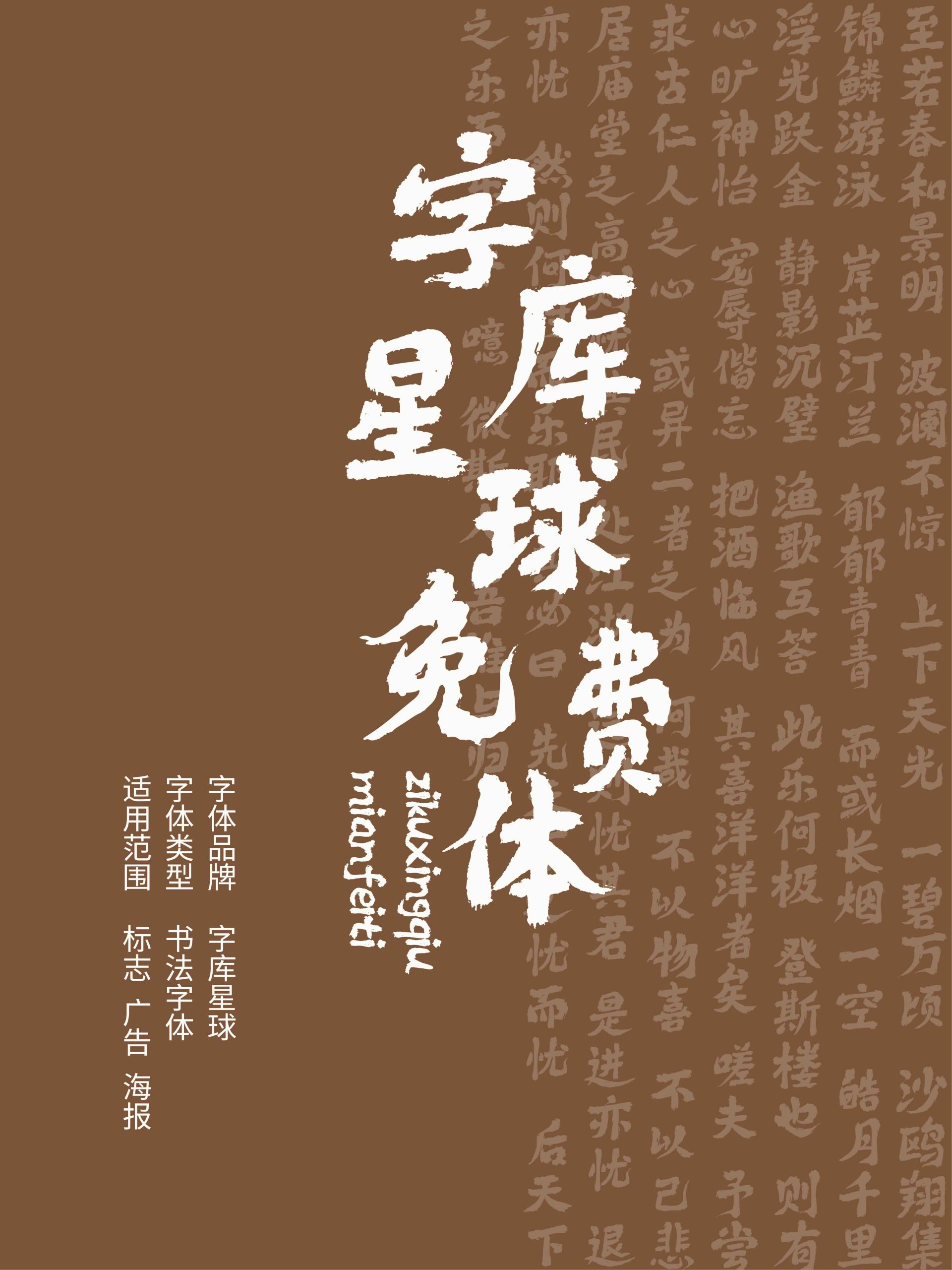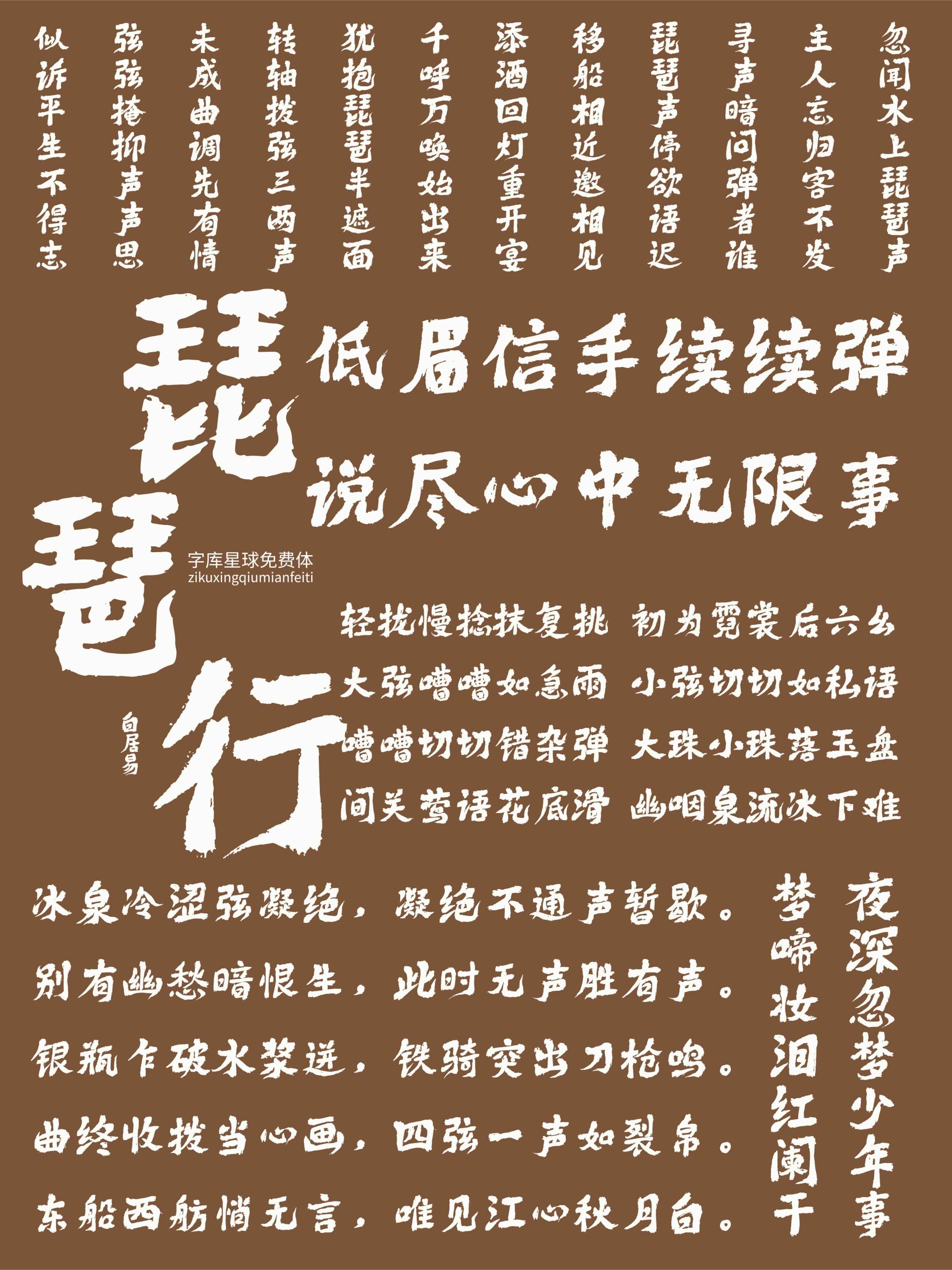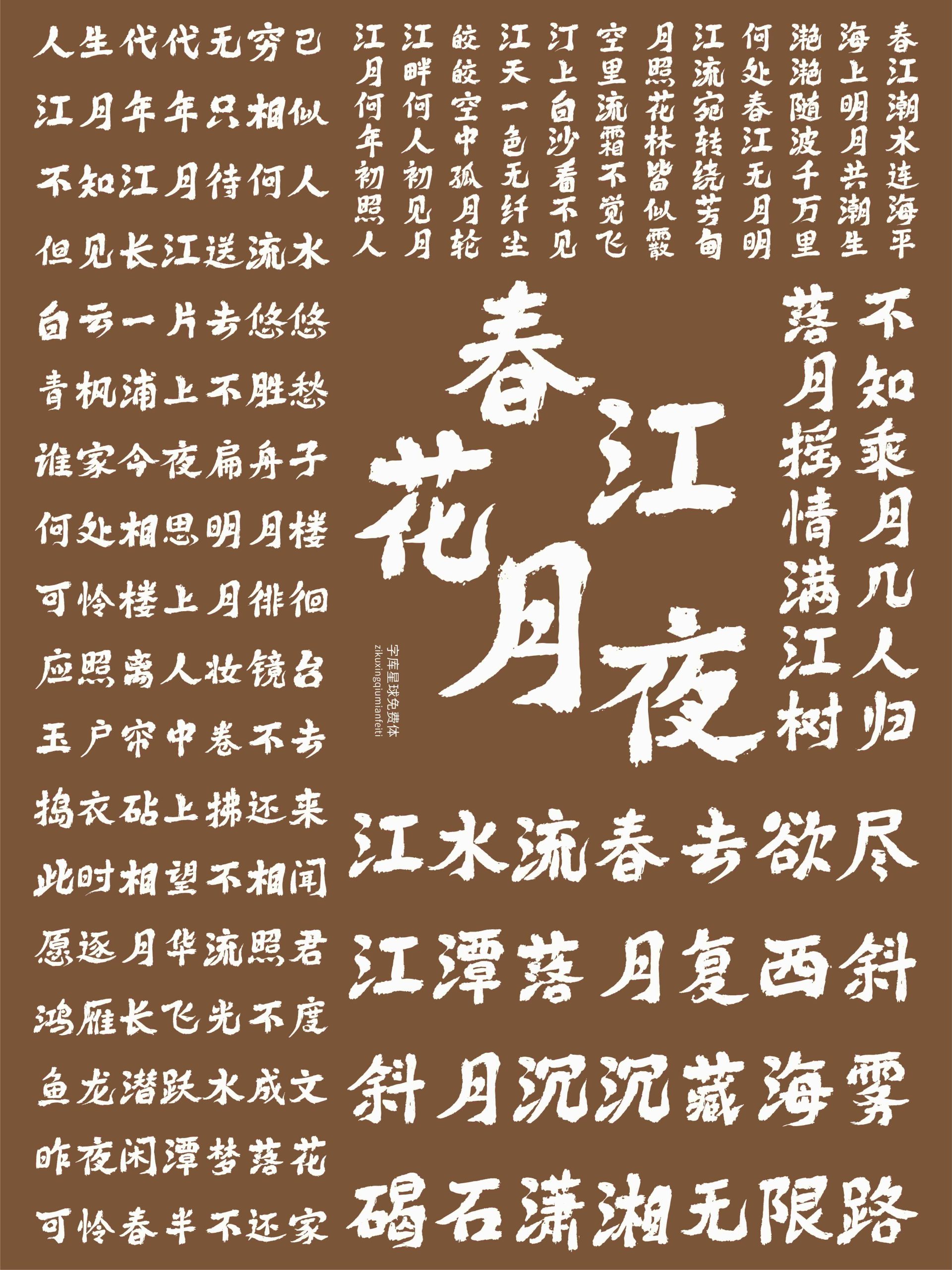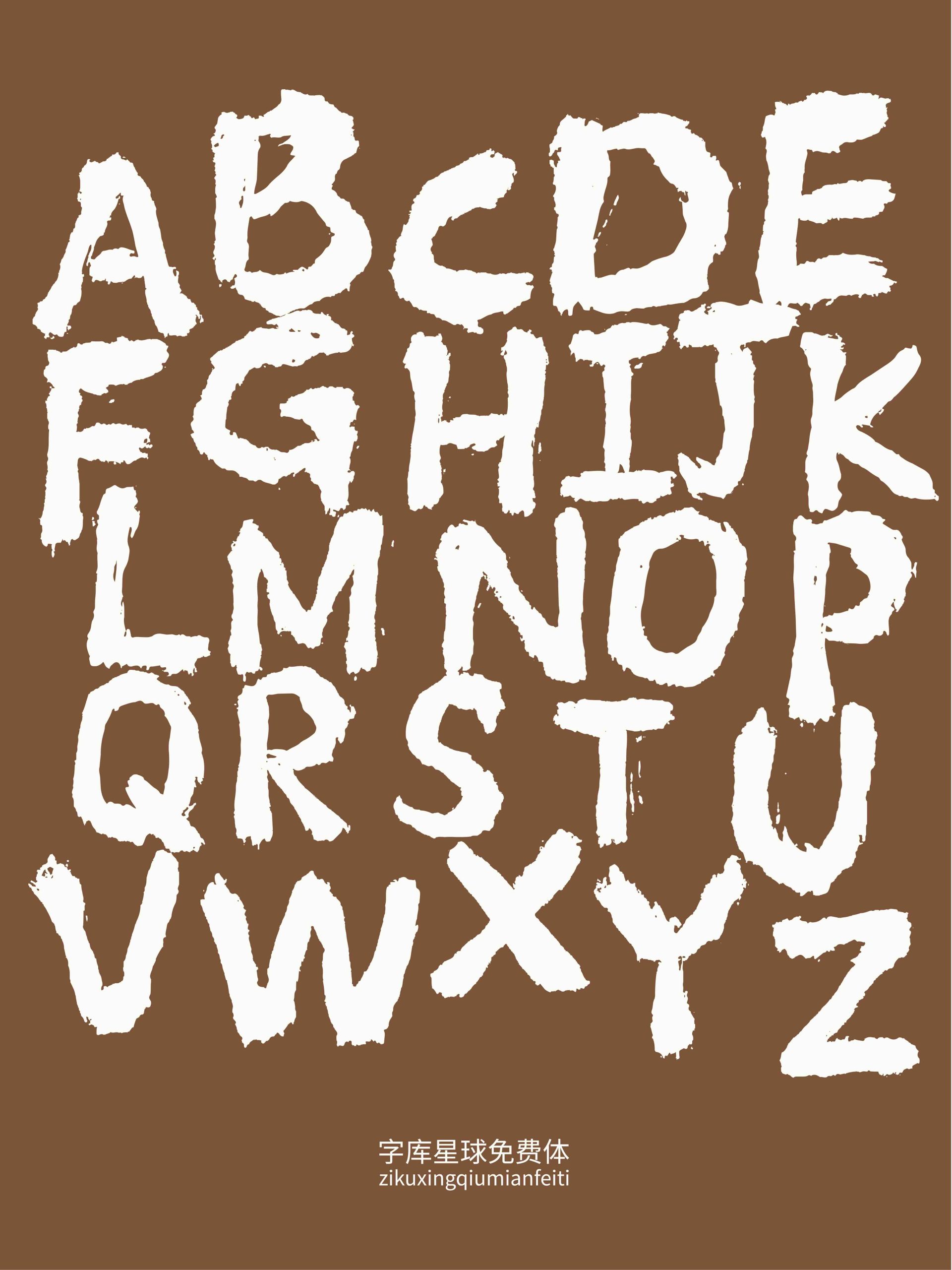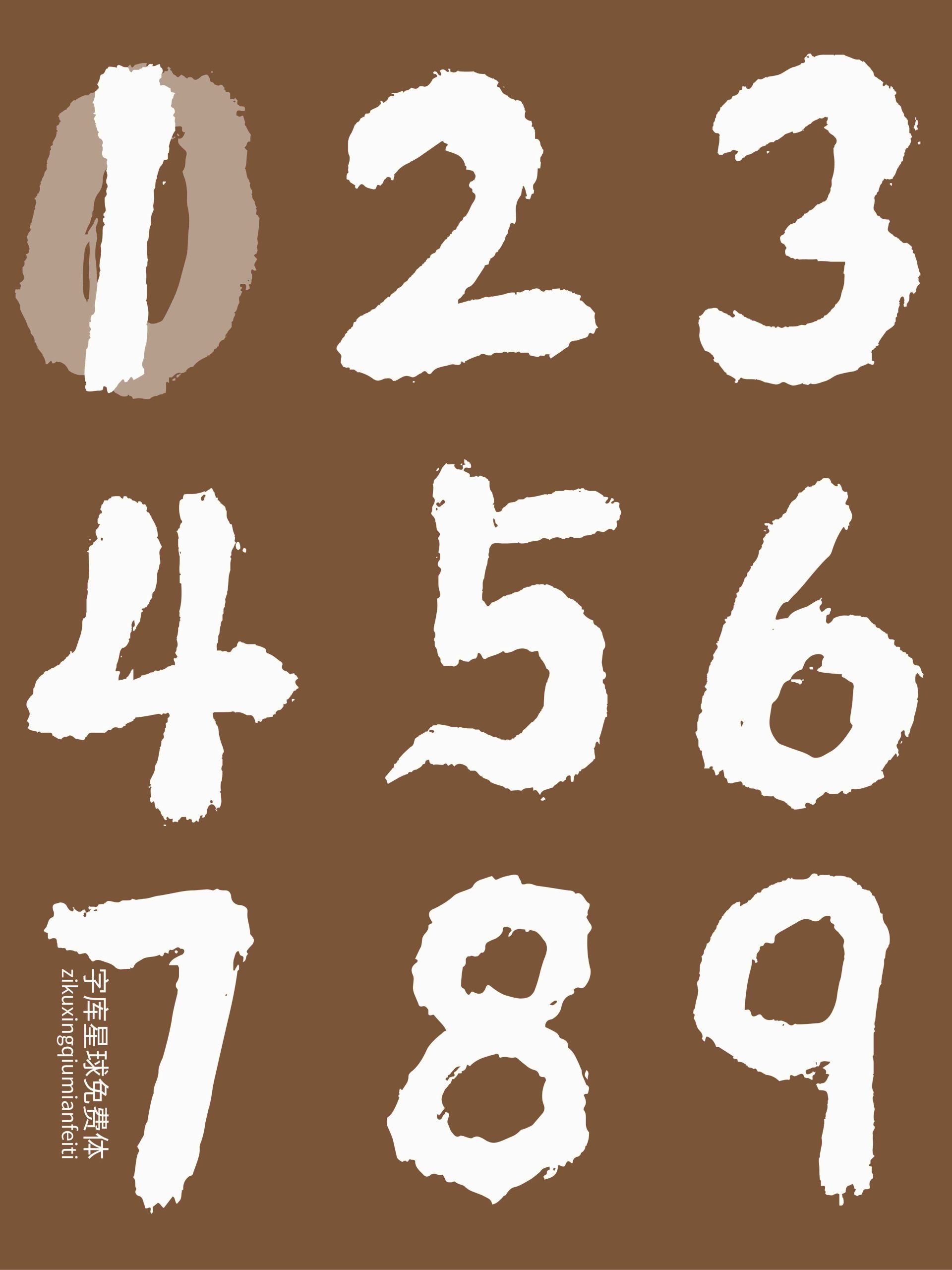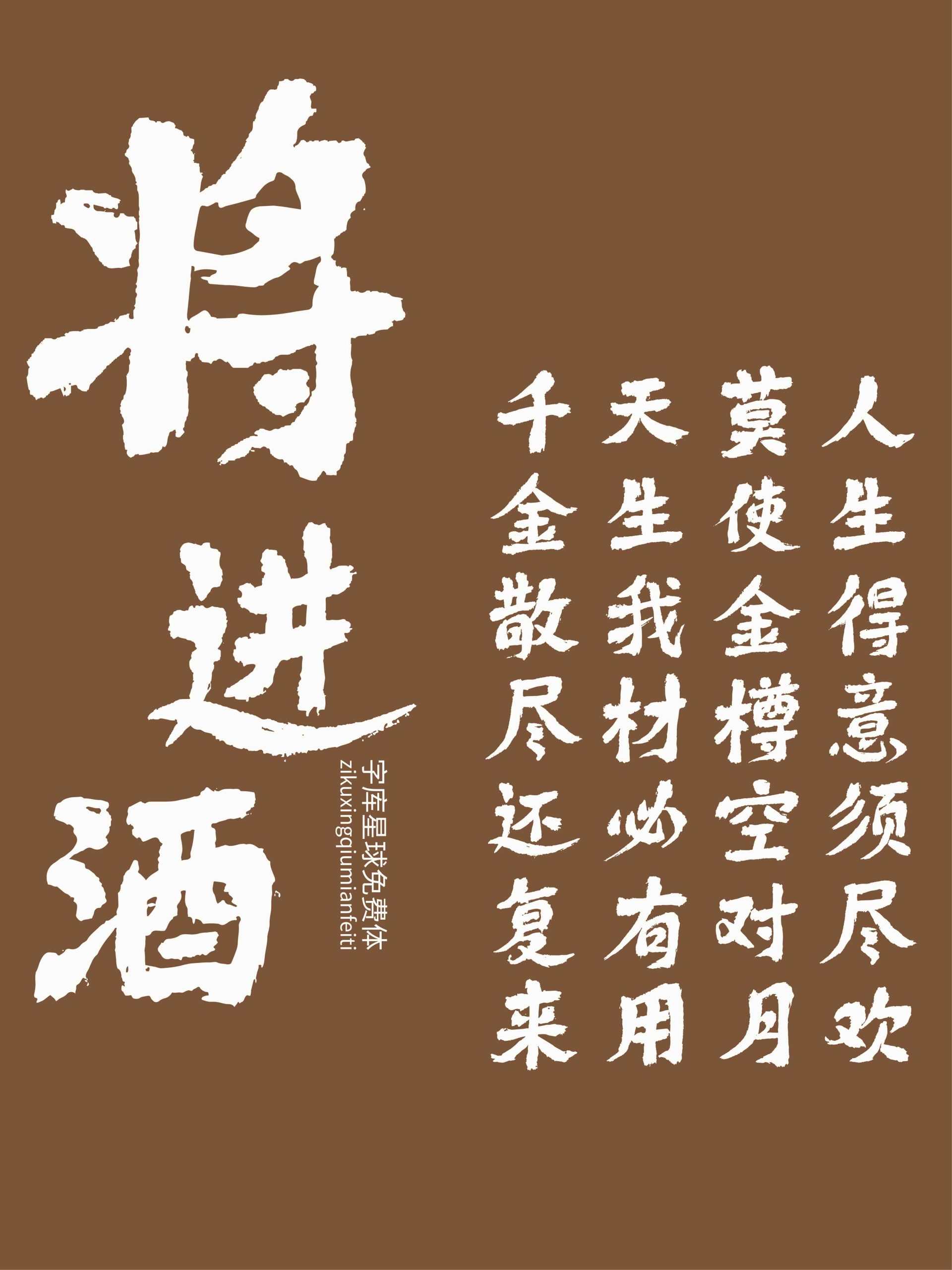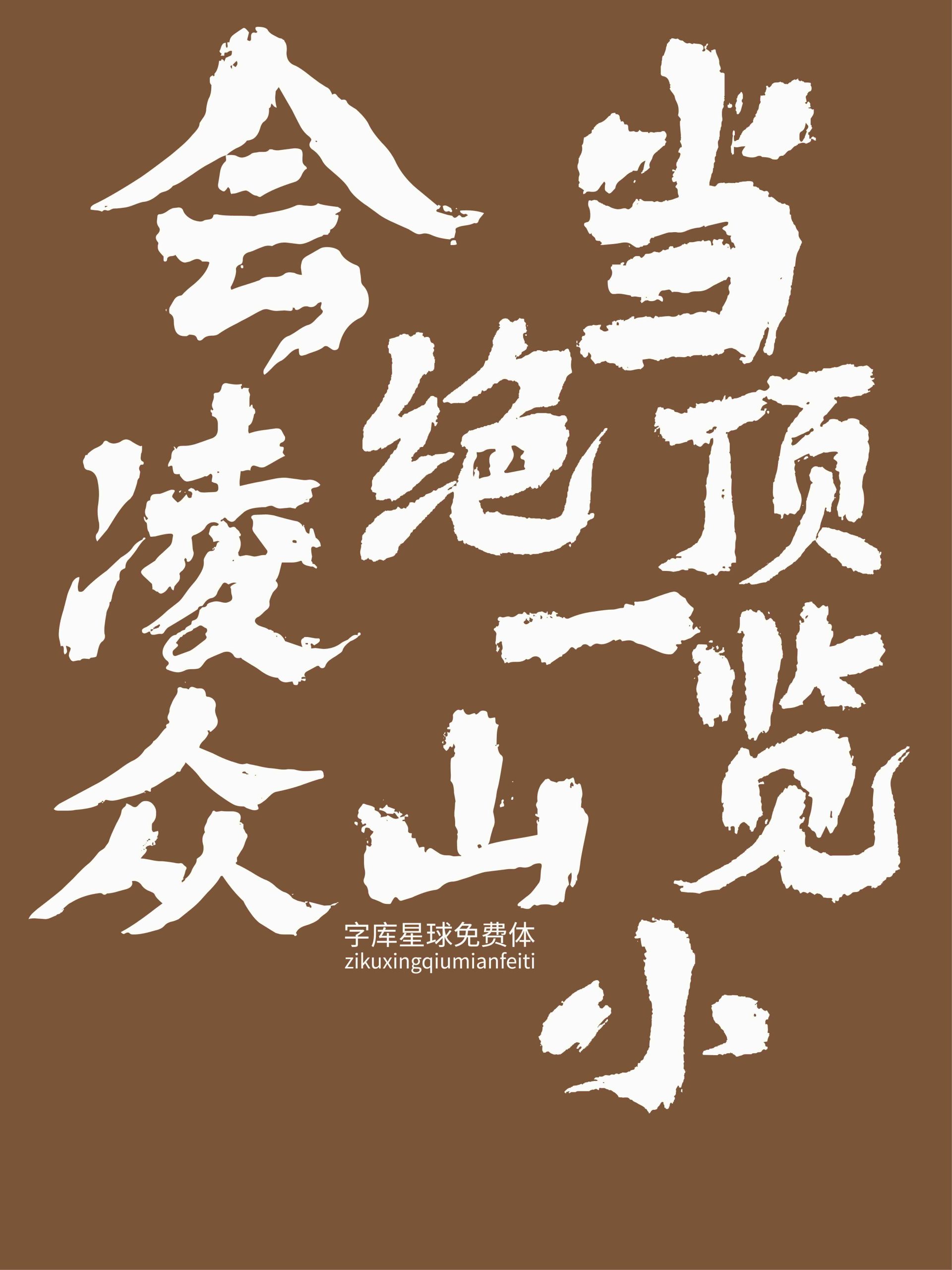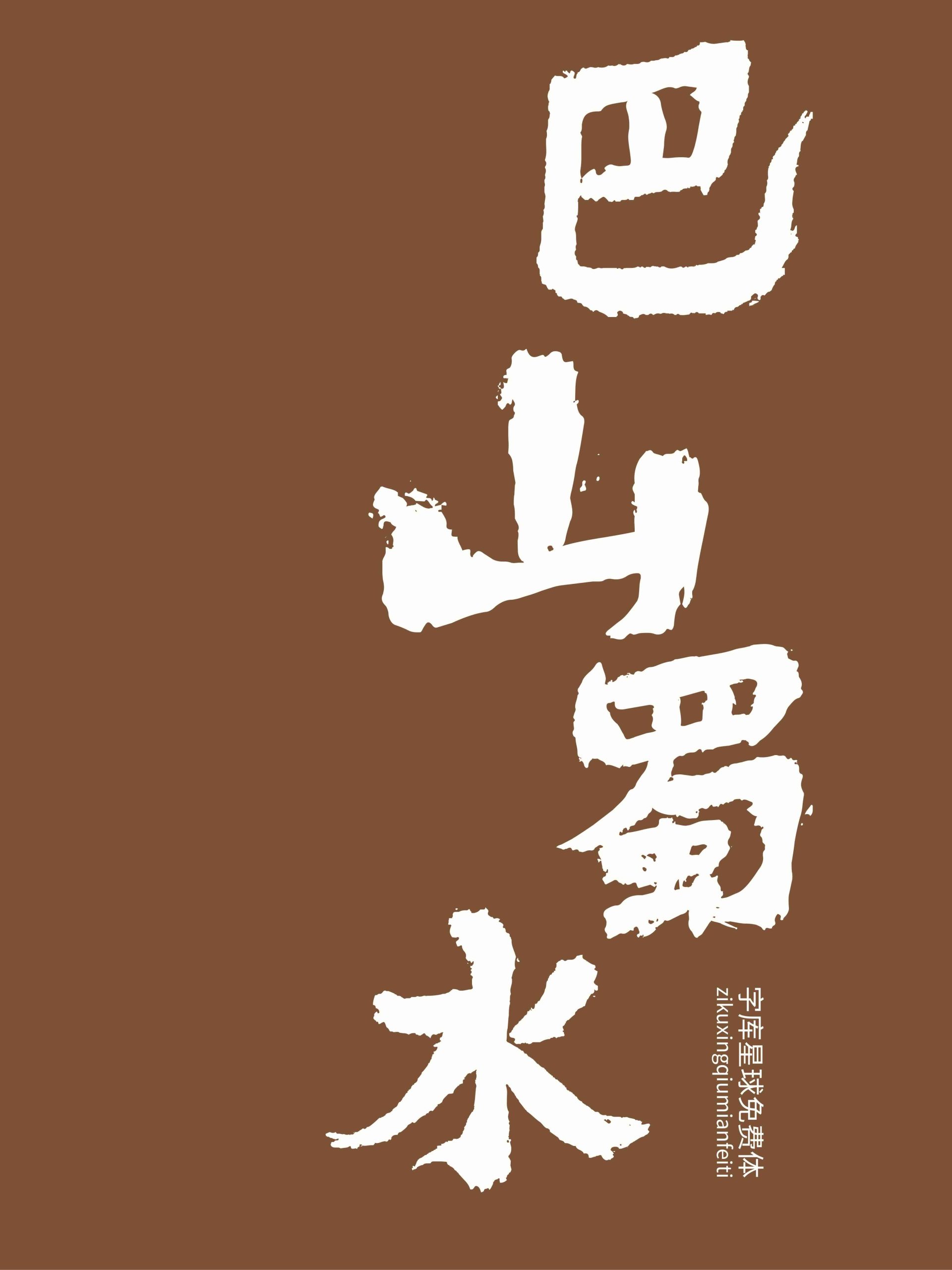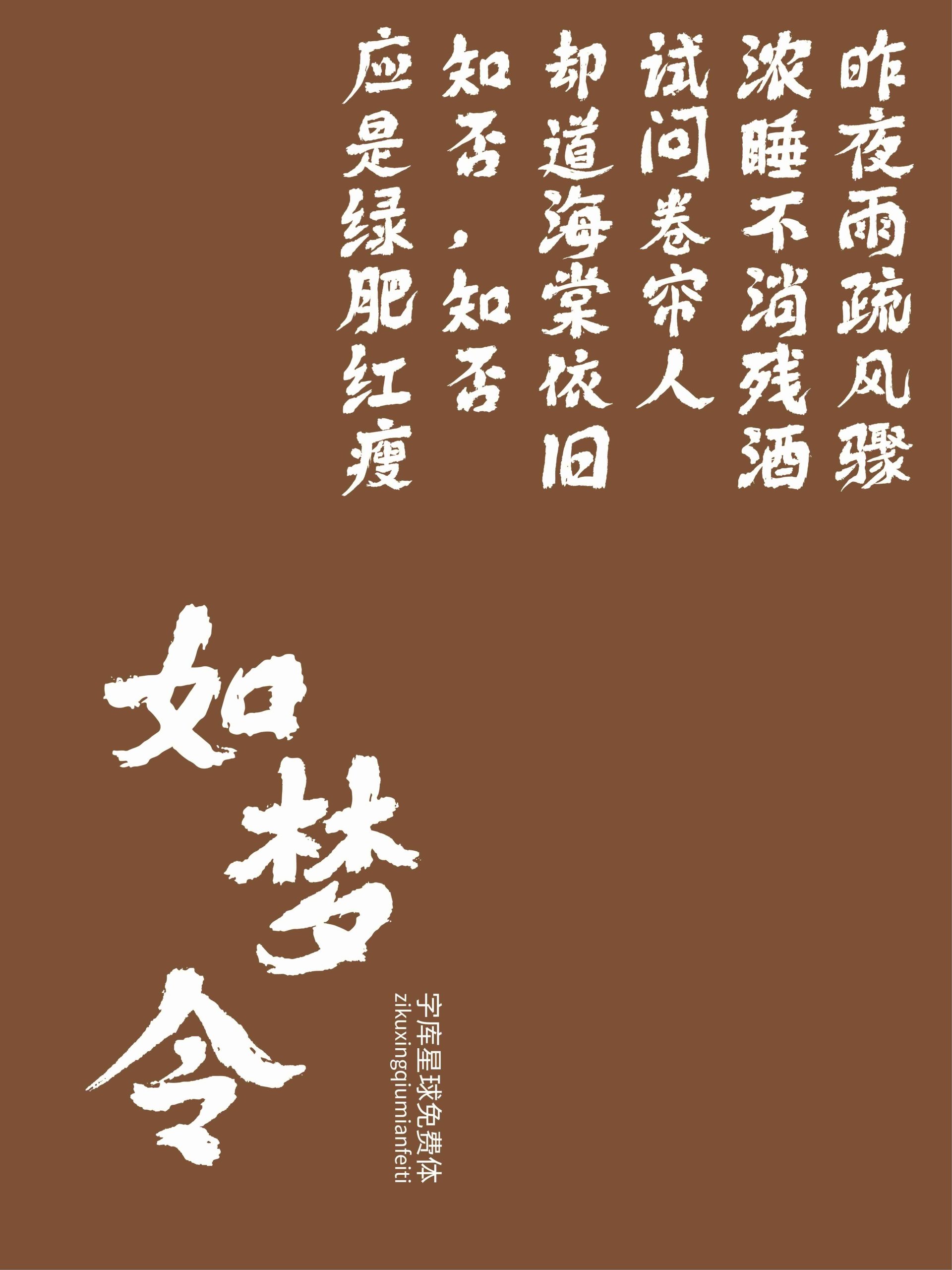
字库星球免费体
在电脑字体越来越规整的今天,手写文字依然拥有独特的情感价值。字库星球免费体的设计灵感来源于日常书写中的自然笔迹,希望将传统毛笔书写中的力度与随性感,以数字字体的形式呈现出来,让更多用户能够在设计中感受到手写文字的温度。
在设计过程中,字体保留了毛笔书写时的轻重变化,通过自然的笔画转折、收笔形态以及略带墨迹感的细节,让每一个字符尽可能保留手写时的自然状态。相比规整的印刷字体,它更加注重书写感与亲和力,在统一结构的基础上,保留了一些自由变化的空间。
字库星球免费体适用于海报标题、文化宣传、品牌包装、社交媒体配图、活动设计等多种场景,也可以用于需要手写感和东方气息的视觉创作中。希望这款字体能够为设计师和创作者提供一种不同的文字选择,让作品多一份自然与温暖的表达。